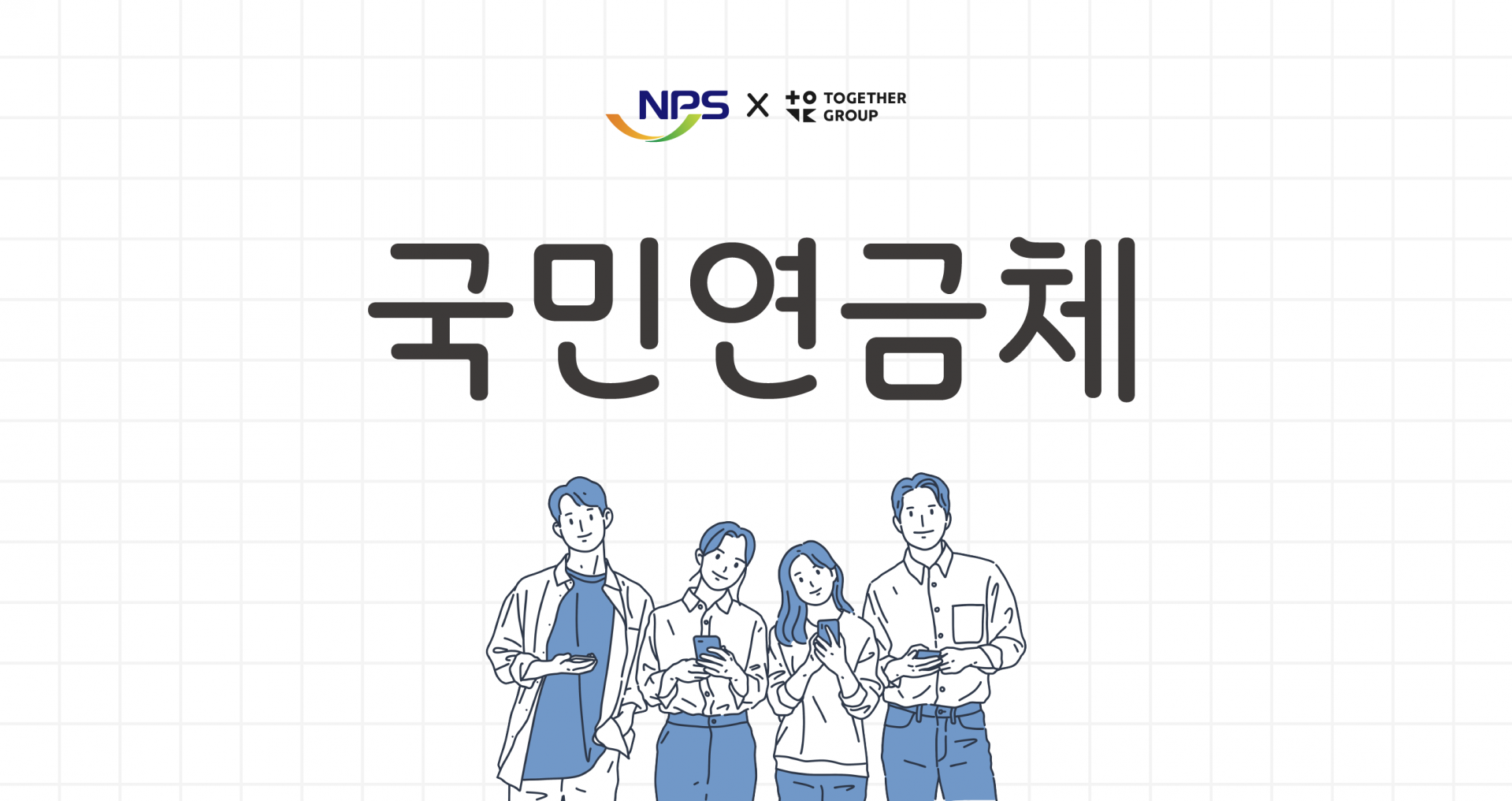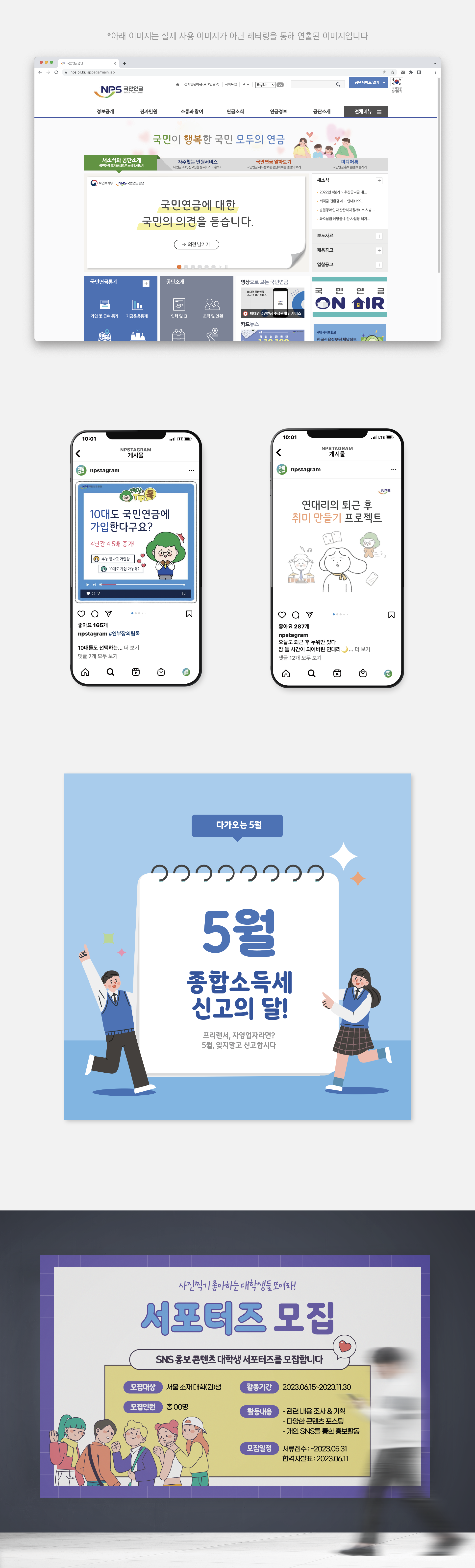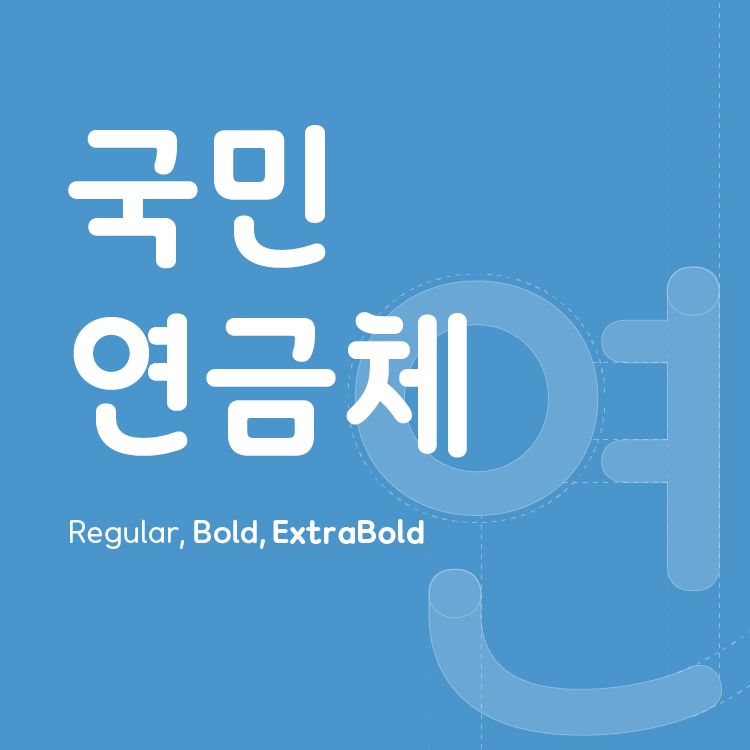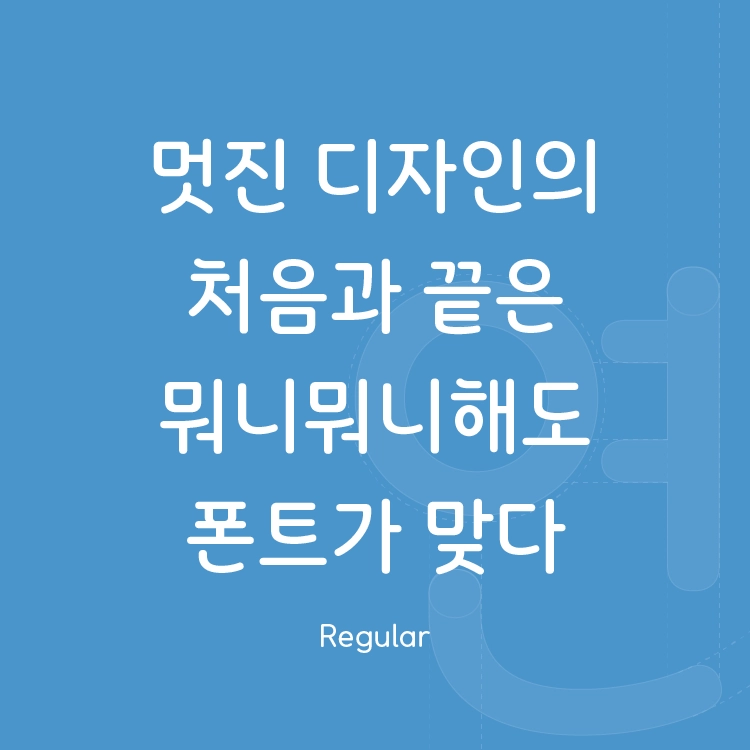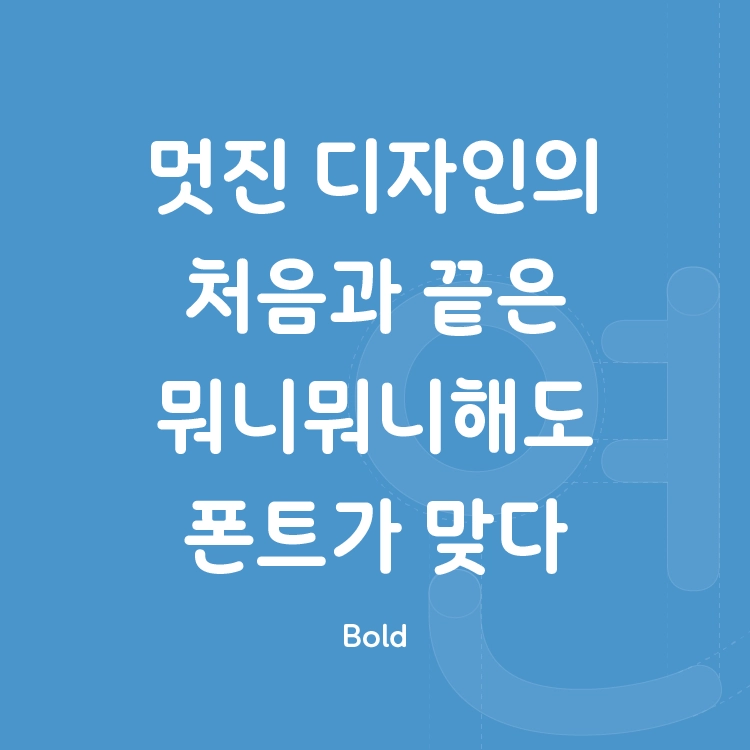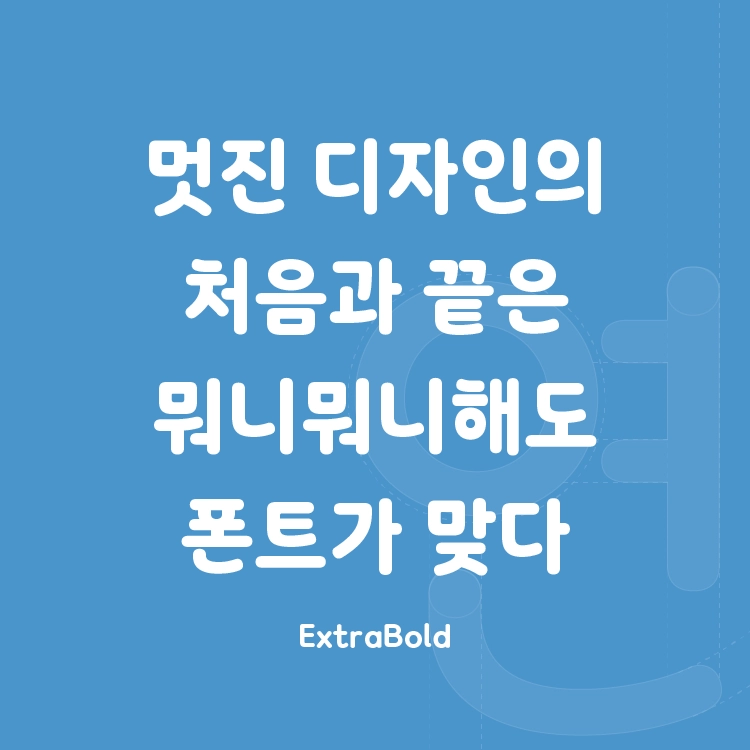
국민연금체
따스하고 포근한 국민연금체
'국민연금체'는 국민연금제도에 대한 인식이 낮은 미래 가입자인 젊은 1020 타깃으로 따스하고 포근한 공단의 기존 브랜드 이미지를 강화한 디자인의 서체입니다.
Regular, Bold, ExtraBold 세 가지 굵기로 구성되었습니다.